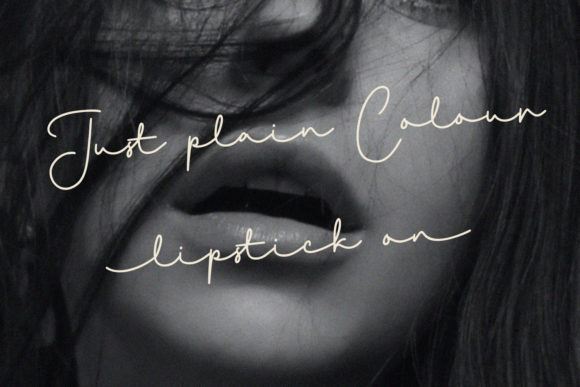
Creativefabrica Mirabille Font
[Creativefabrica] Mirabille Font
Мирабиль - это сладкий, нежный и плавный шрифт сценария.
Он выглядит потрясающе на свадебные приглашения, благодарственные открытки, цитаты, поздравительные открытки, логотипы, визитные карточки и любой другой дизайн, который нуждается в индивидуальном подходе.